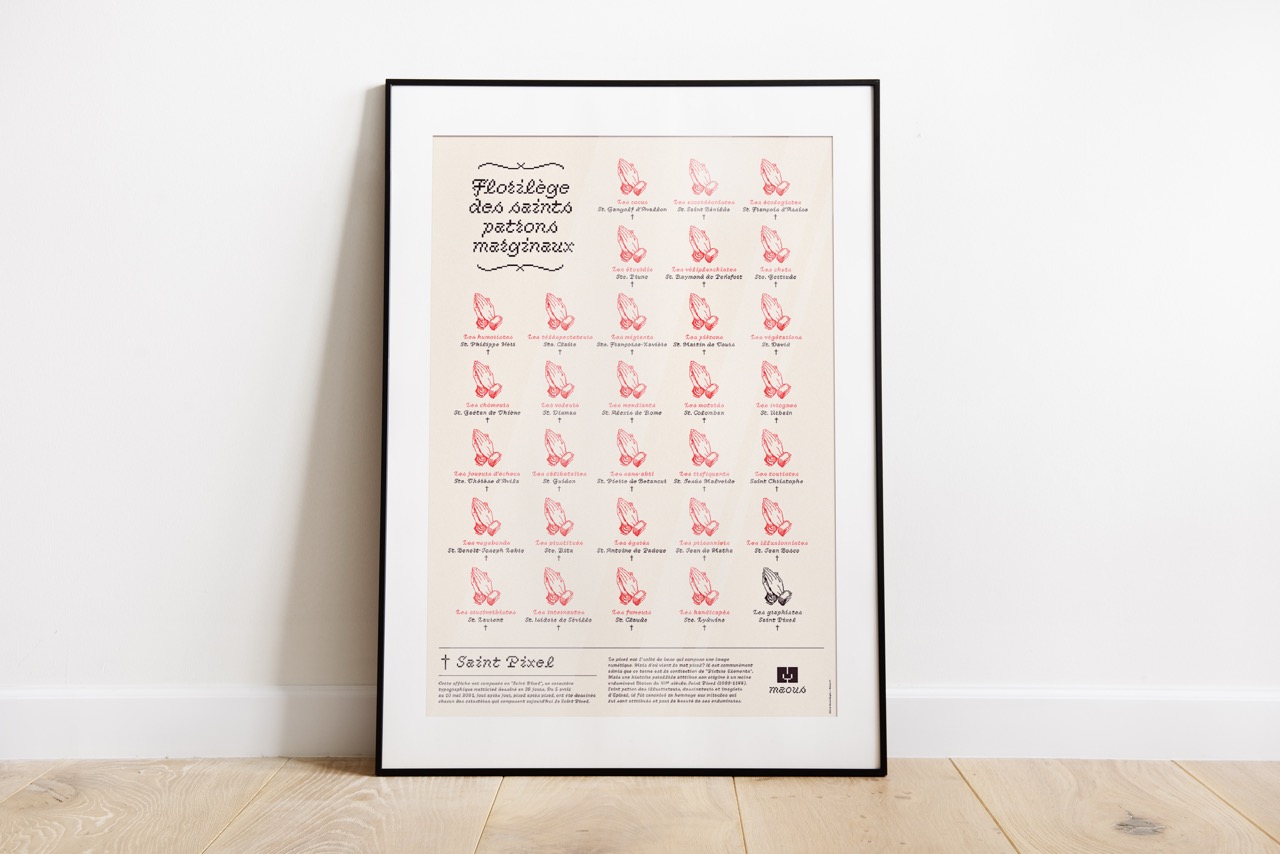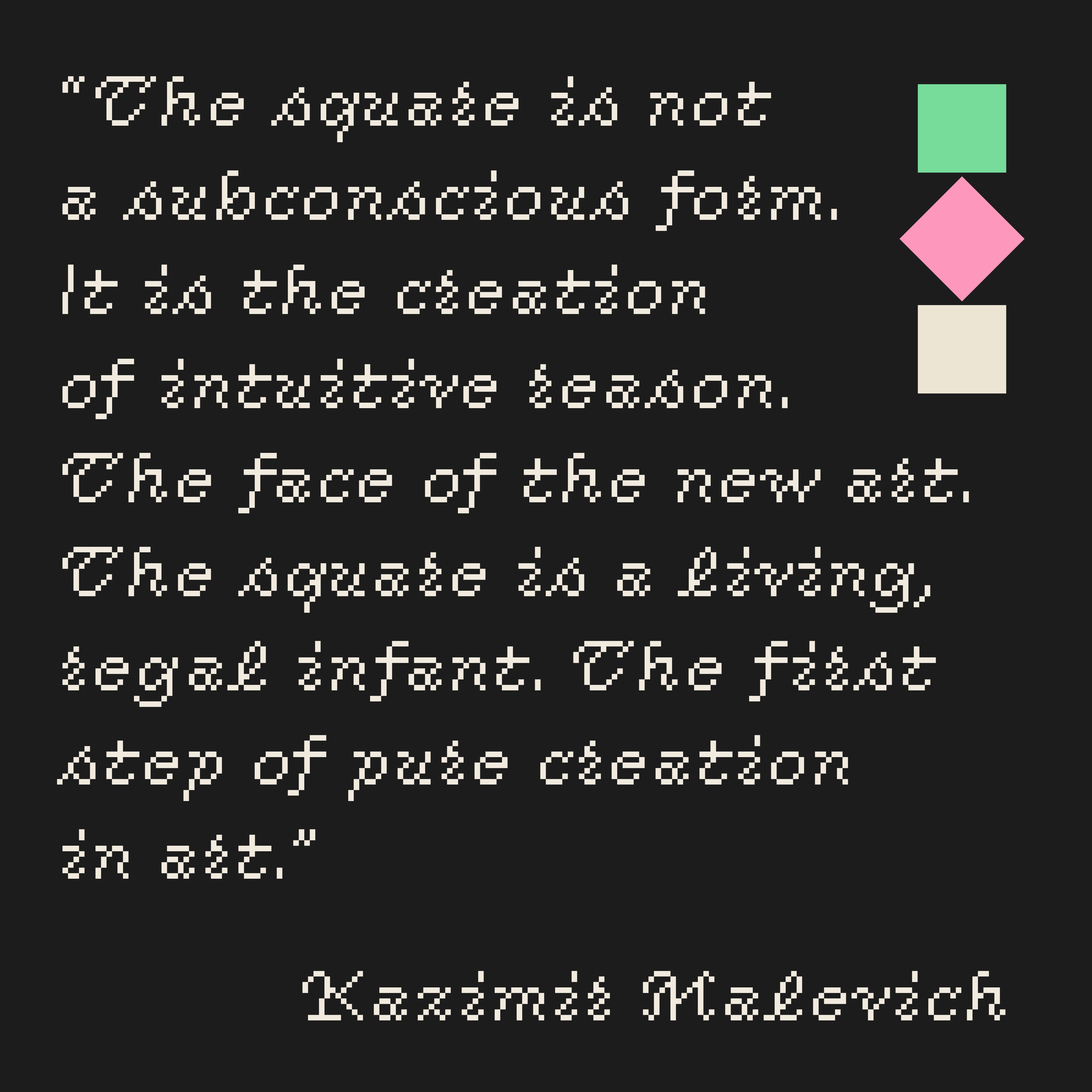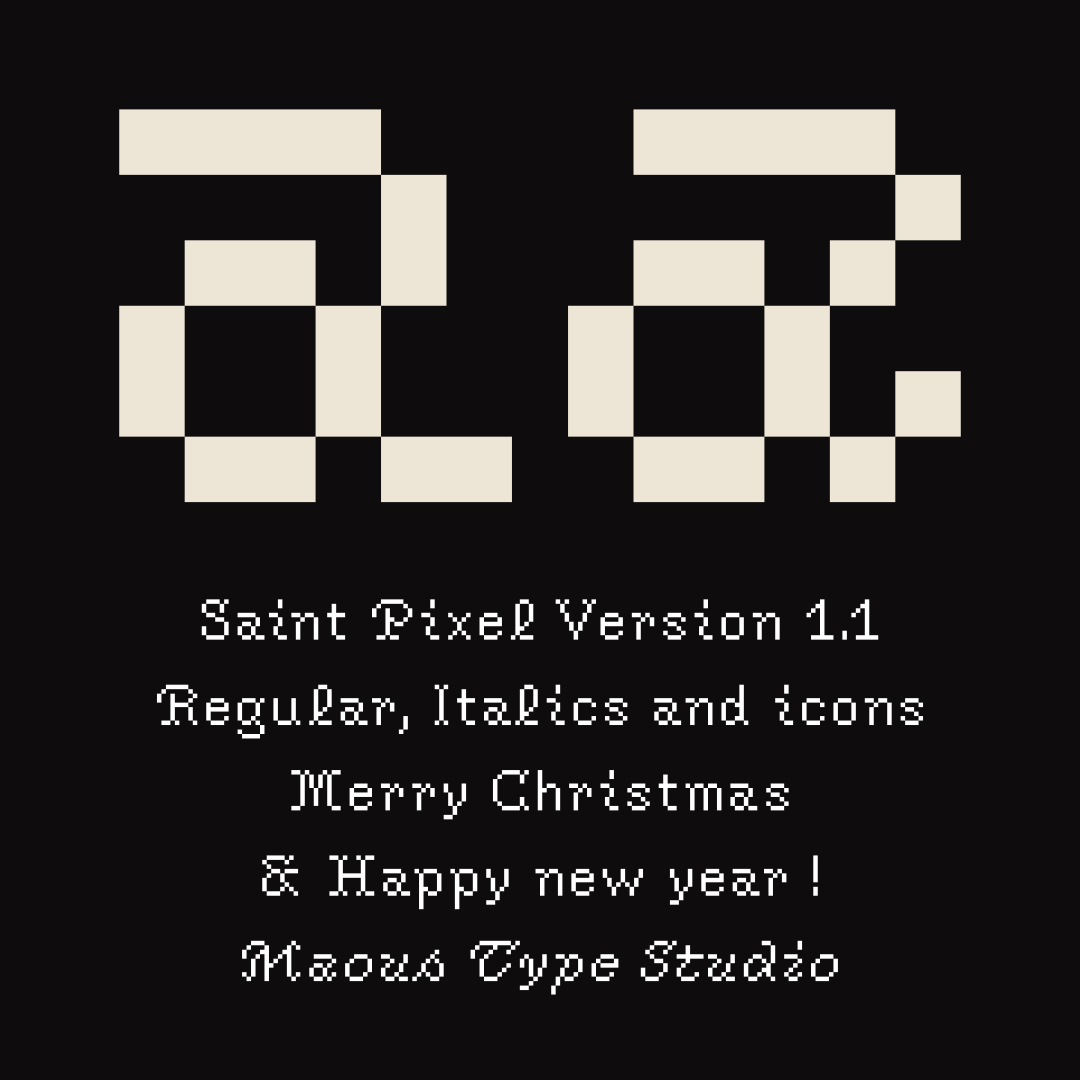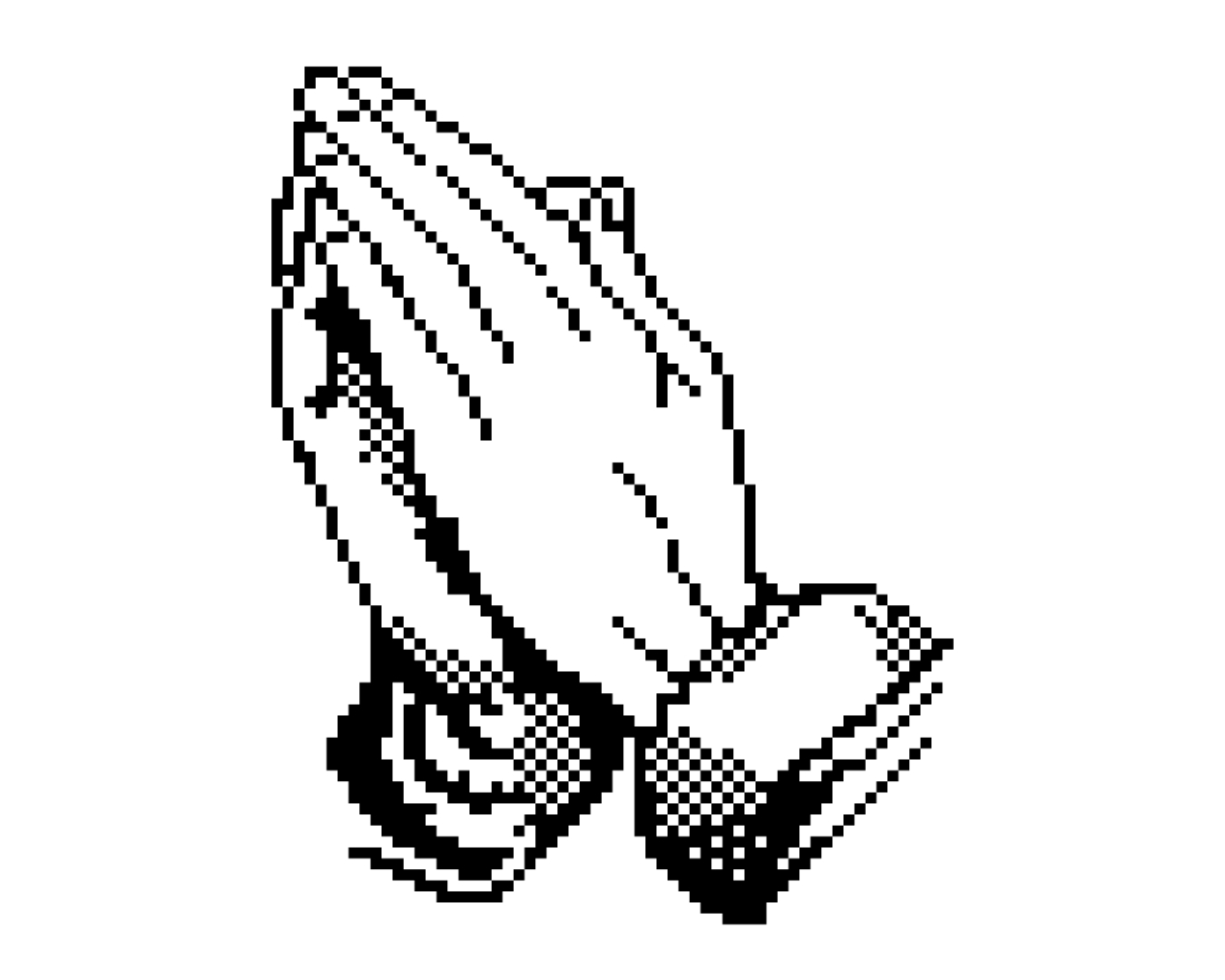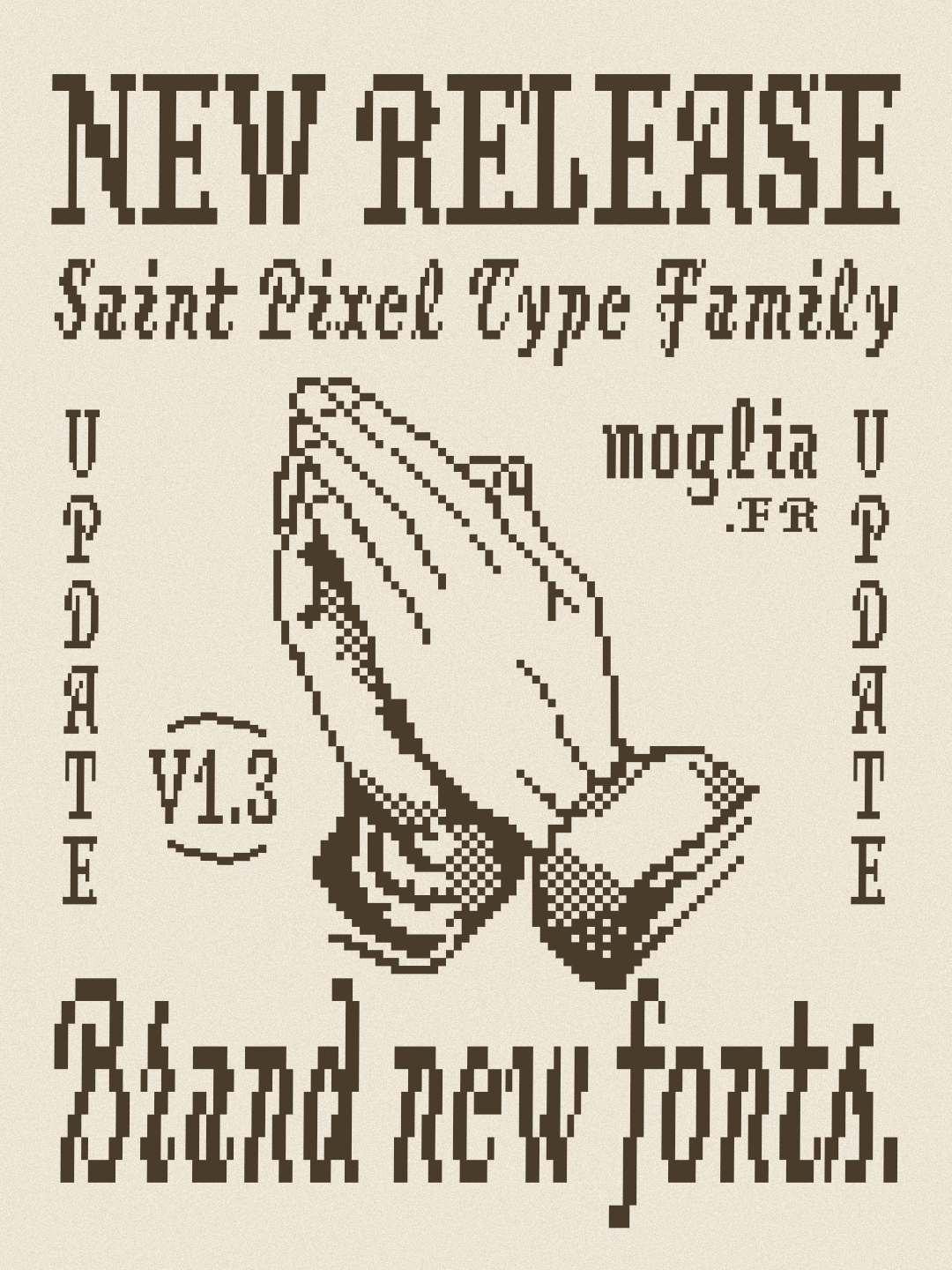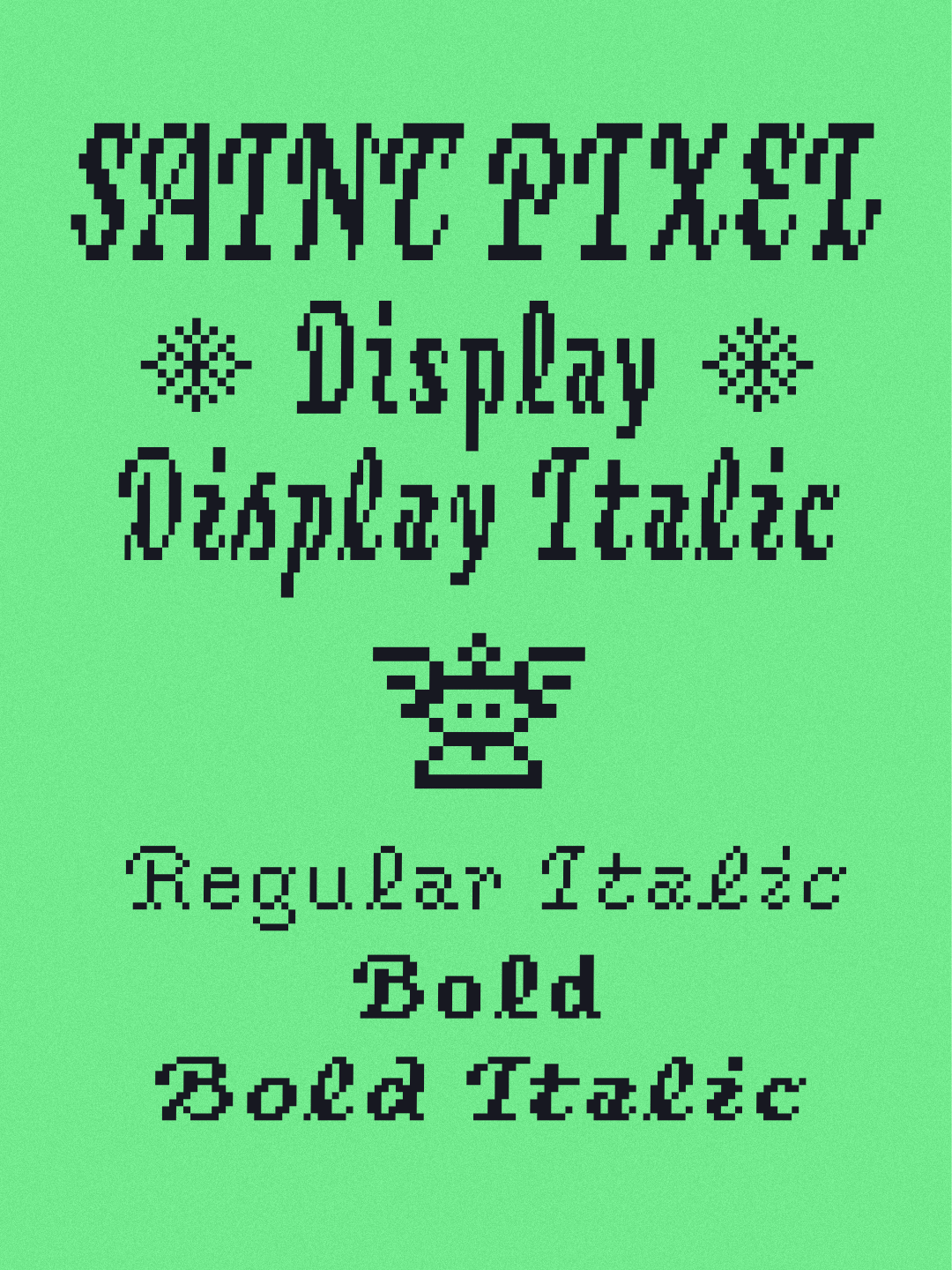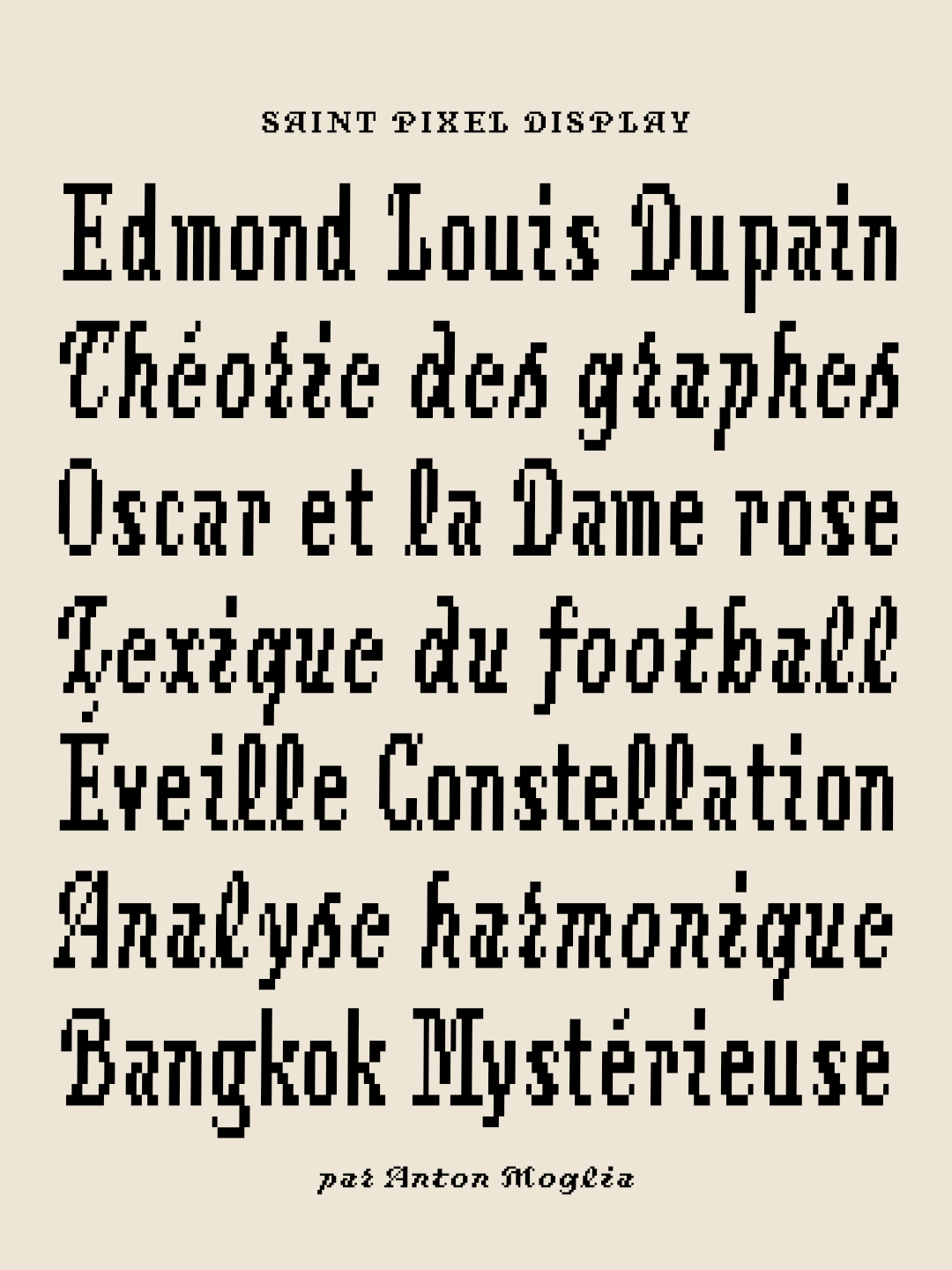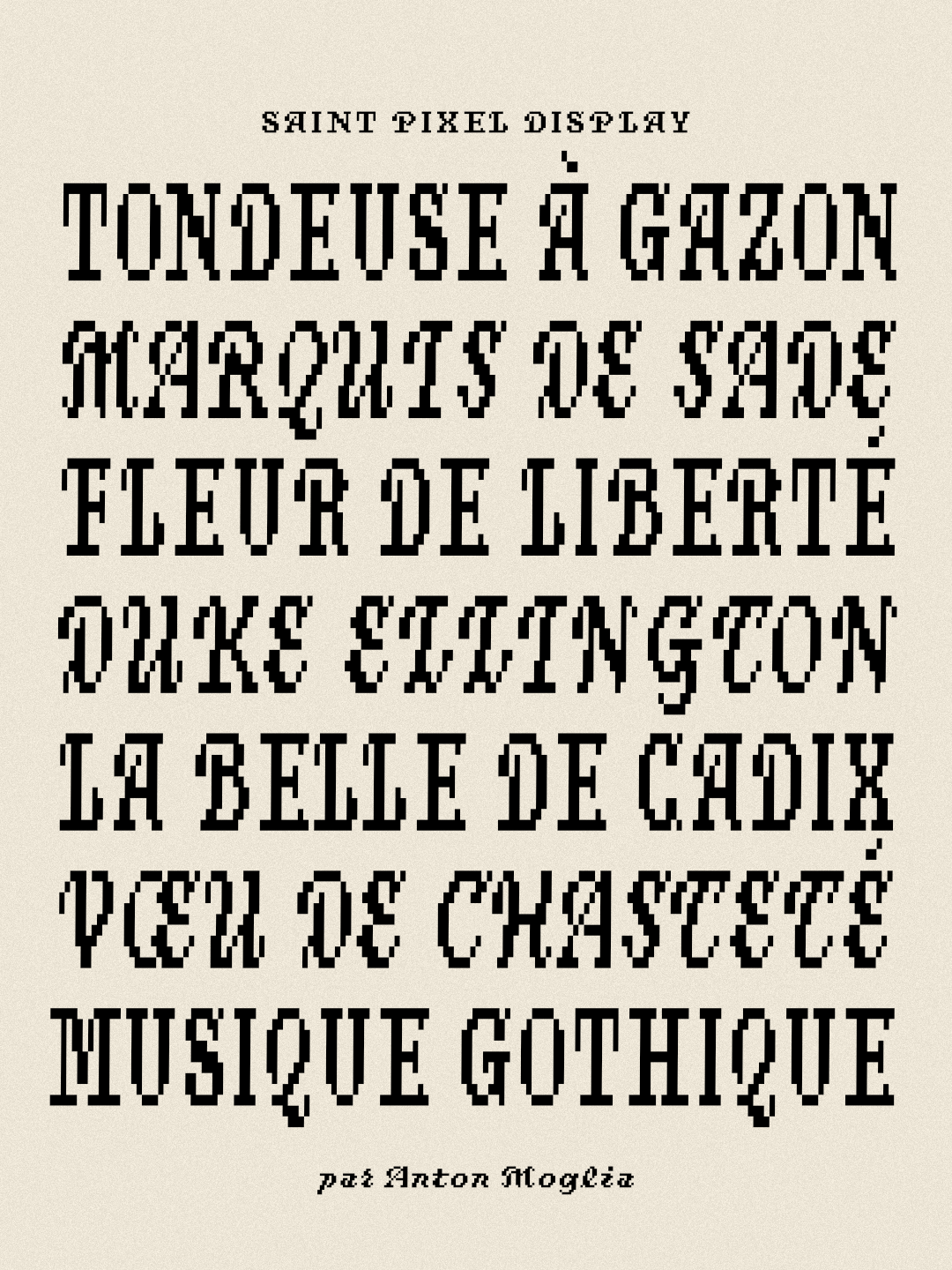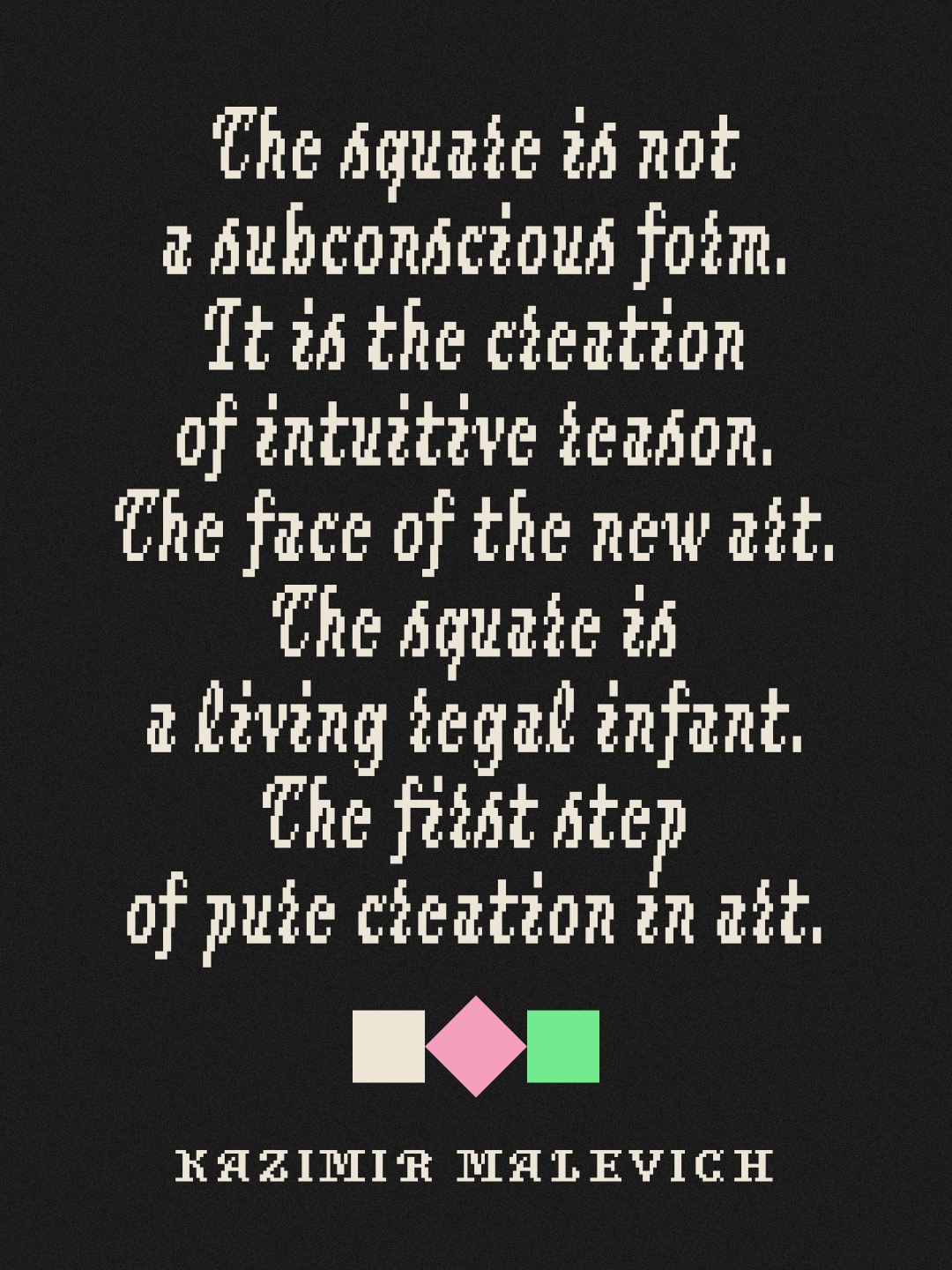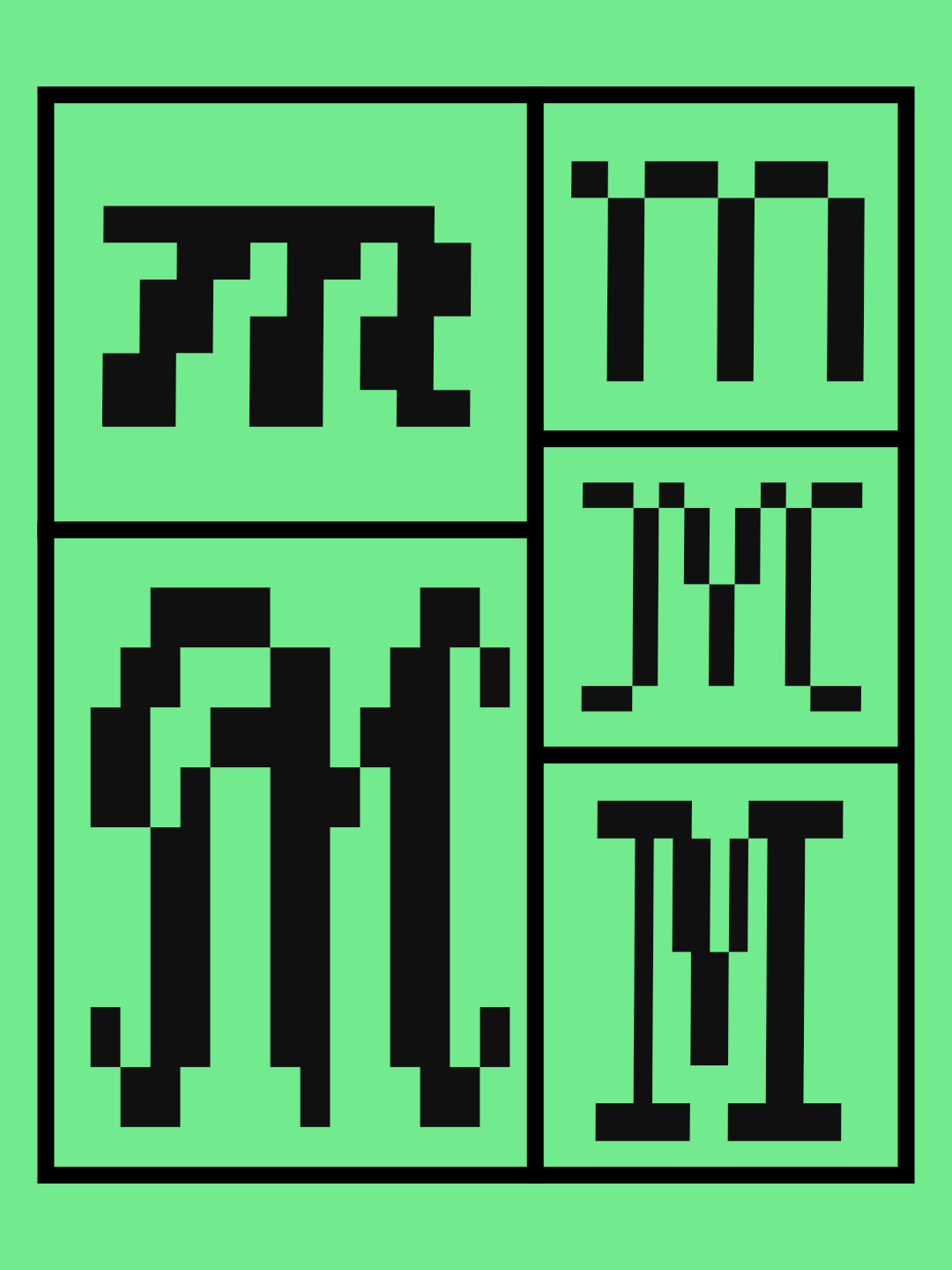
Saint Pixel
Regular, Bold, Italics & Display versions
Saint Pixel, une fonte au style « point de croix » mêlant esthétique pixel et broderie. Disponible en Regular, Italic, Bold, Bold Italic, Display et Display Italic, elle inclut des glyphes de Noël exclusifs.
Designer Anton Moglia